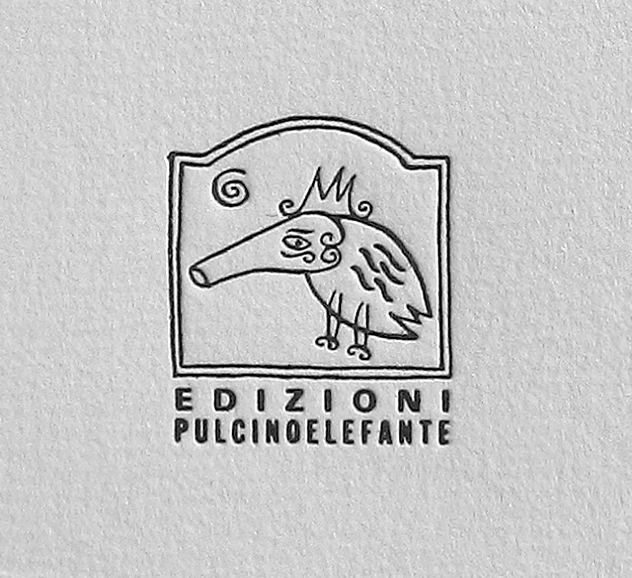
Alberto Casiraghy e Pulcinoelefante
Tutti prima o poi piantano un sogno.
Alberto Casiraghy e l’avventura delle edizioni Pulcinoelefante
La mostra celebra il lavoro e la figura di una personalità unica, Alberto Casiraghy, che ha attraversato con il suo passo inconfondibile (e la sua ineffabile gentilezza) i territori della poesia, dell’editoria, dell’arte e della letteratura. La sua traiettoria di vita impressiona per la coerenza e la tenacia pressoché inesauribili nel perseguire ciò che si è intrapreso.
Nata nel 1982 a Osnago, la piccola ma rizomatica casa editrice di libri d’artista Pulcinoelefante è un caso a sé sia per le dimensioni incredibili del catalogo che per l’originalità, la tenuta nel tempo e la ricchezza di connessioni culturali e sociali implicate. Ha affascinato generazioni di artisti, collezionisti, appassionati della stampa e dell’editoria, collezionisti e semplicemente fan.
Gli ingredienti della vicenda – oltre alla passione, alla cura e alla generosità del tipografo – sono una macchina Audax Nebiolo, la carta Hahnemühle, la composizione con i caratteri mobili, le incisioni su legno di bosso di Adriano Porazzi, e il formato chiuso mai variato di 13,5 x 19,5 centimetri per otto pagine, frontespizio compreso. L’agilità di questo vettore è stato un terreno d’elezione naturale per il linguaggio degli aforismi.
Le edizioni Pulcinoelefante sono molto di più di un progetto editoriale: è la creazione – con tenacia e orgoglio ma senza arroganza – di un universo poetico inclusivo e dirompente, capace di attingere alle sorgenti del profondo facendo leva sul concetto di agilità e portabilità, una sorta di gioioso nomadismo, incurante di steccati, censure e logiche preconfezionate ratificate dal mercato.
Per raccontare la sua vicenda umana e artistica, i curatori hanno deciso di restituire almeno in parte l’atmosfera dello studio di Osnago, facendo sentire le corde di un luogo che è fisico e mentale al tempo stesso. In mostra, oltre ai famosi libretti, ci saranno opere d’arte, sculture, oggetti, maschere africane dalla collezione privata dell’artista, memorabilia e un reportage in bianco e nero della fotografa di Odessa Anna Golubovskaja realizzato espressamente per la mostra (è di Anna il ritratto di Alberto qui pubblicato). Le fotografie sono analogiche, sviluppate e stampate con procedimento chimico. Un modo per accordarsi allo spirito del Pulcinoelefante e della Tipoteca Italiana, entrambi luoghi che lavorano sul tempo lungo.
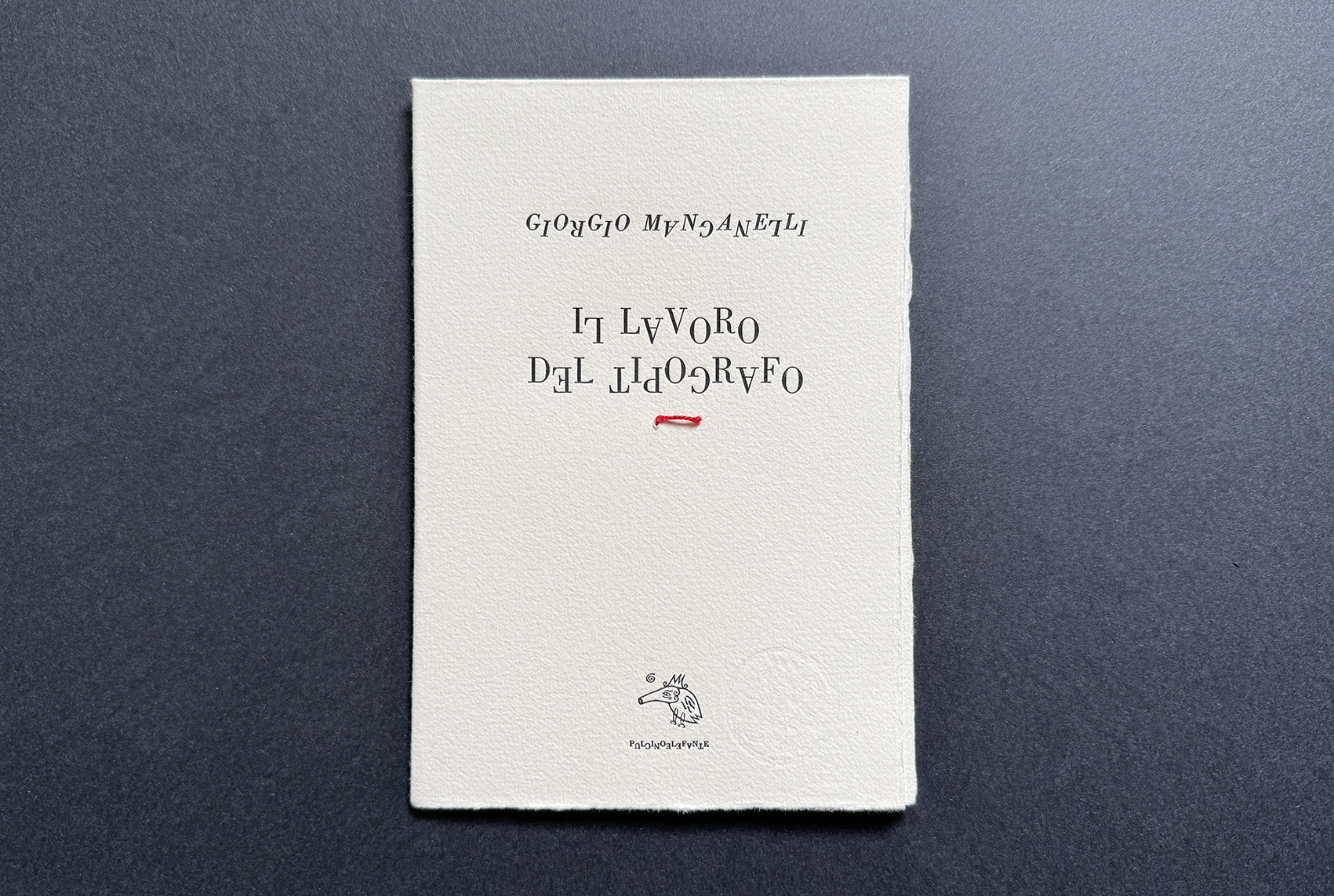
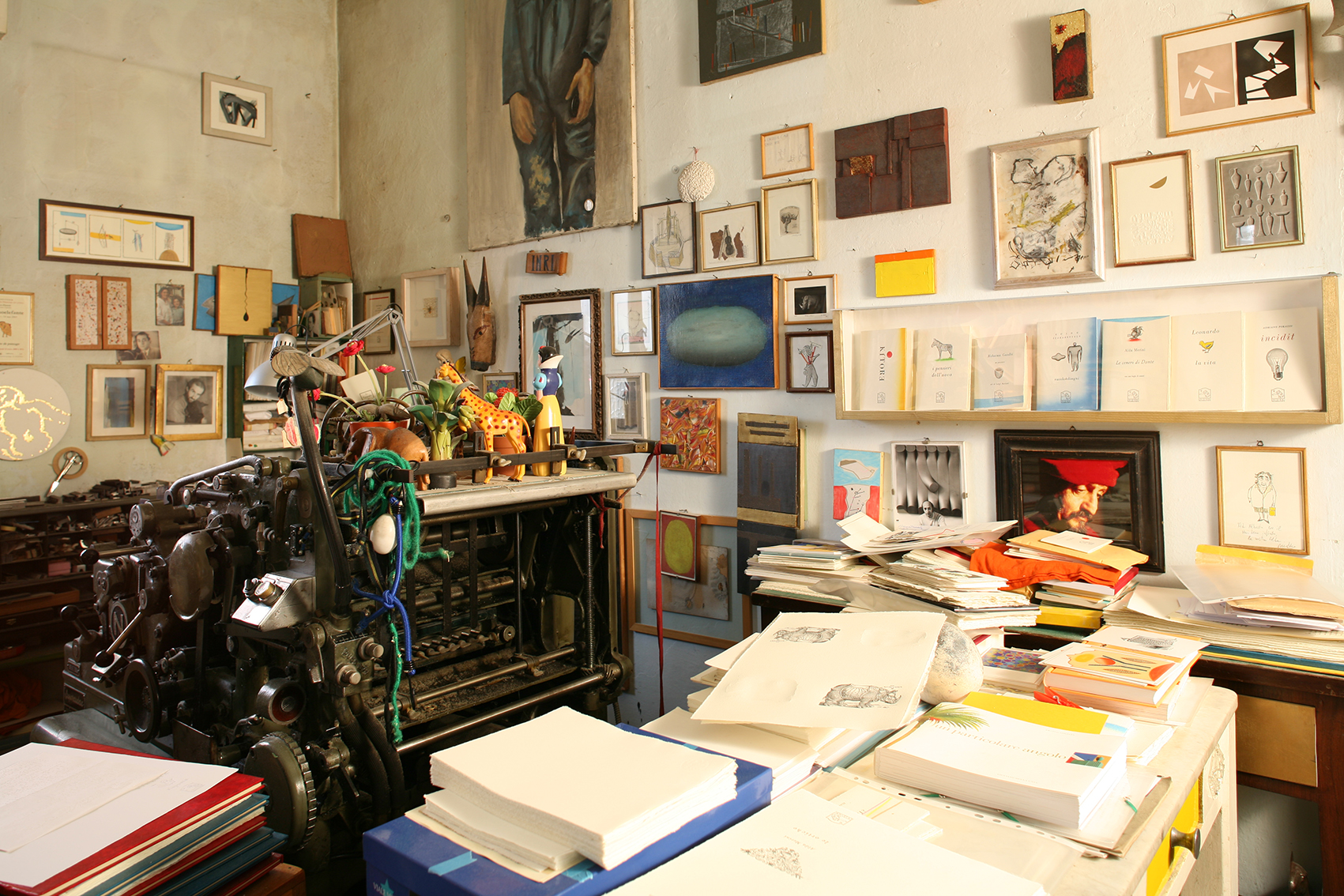
Alberto Casiraghy (1952), liutaio, amante del violino, dei disegni e della poesia, ha lavorato a lungo in una tipografia imparando i segreti del mestiere, per dare vita alla casa editrice Pulcinoelefante, basandosi per il nome e il logo su un buffo schizzo del fantastico animale, fatto quando era bambino.
Dal 1982 ha pubblicato oltre 10 mila piccole plaquettes composte da un testo – una breve poesia, anche solo un verso o una rima, una riflessione, un aforisma – accompagnati da piccole incisioni o disegni originali eseguiti da artisti, anche molto importanti. Fra gli autori si contano tanti nomi illustri, non solo italiani: Campana, Gadda, Pasolini, Penna, Merini, Kafka, Cocteau… E tra gli artisti Munari, Cattelan, Baj, Tadini, Paladino, Mainolfi, Parmiggiani, Isgrò, Nespolo.